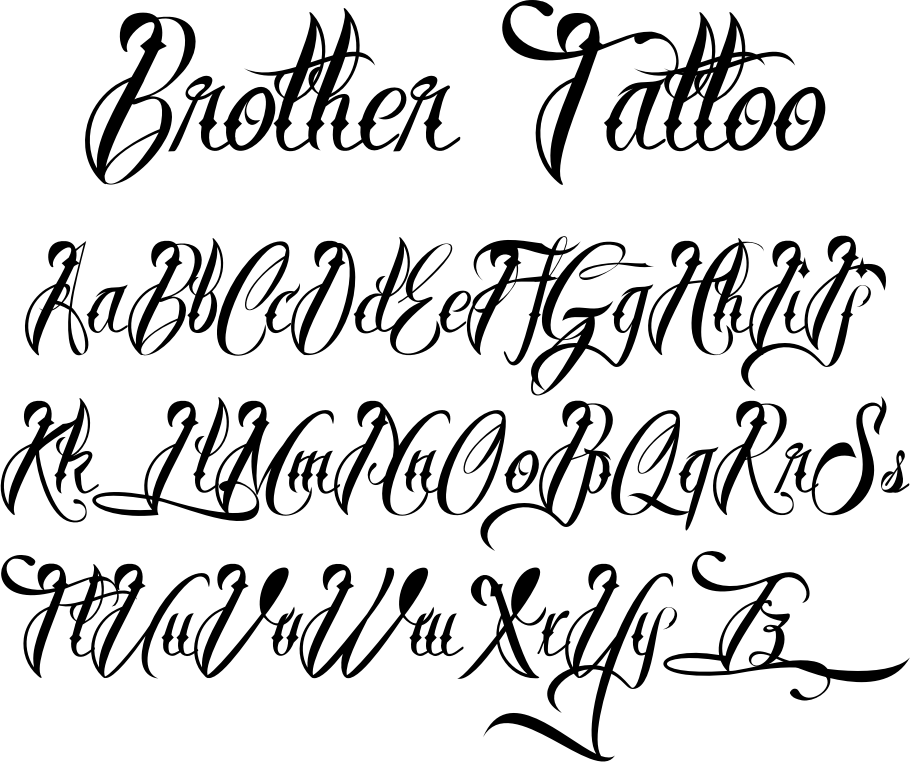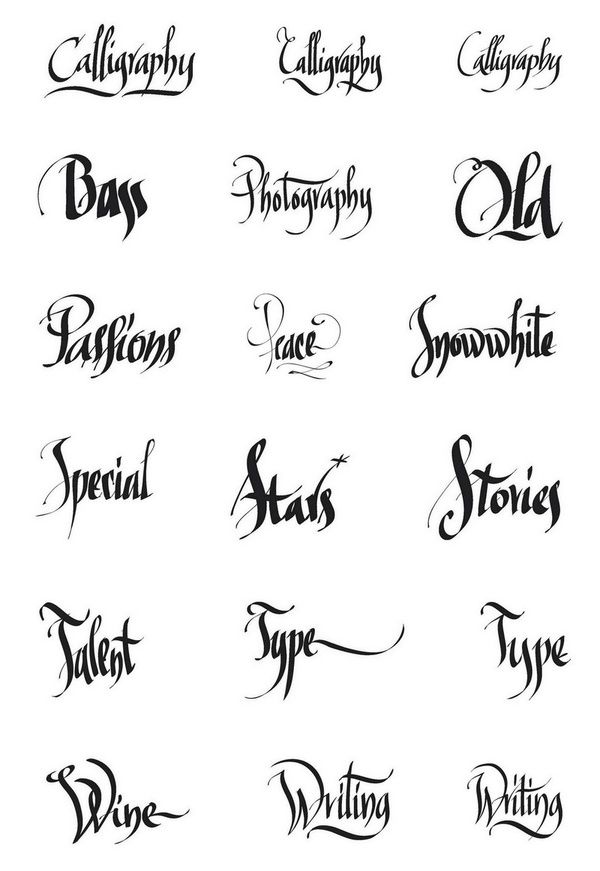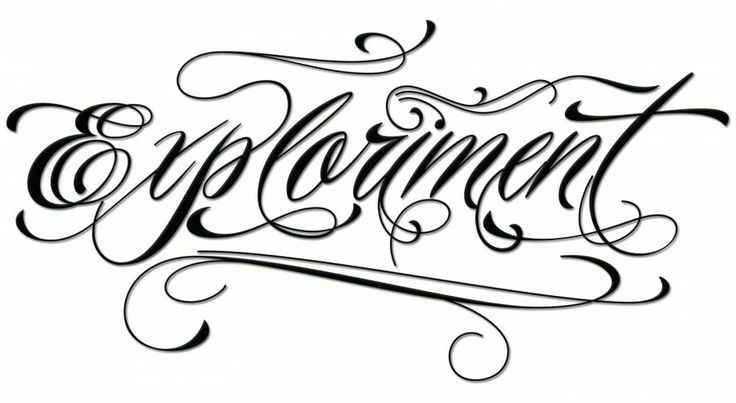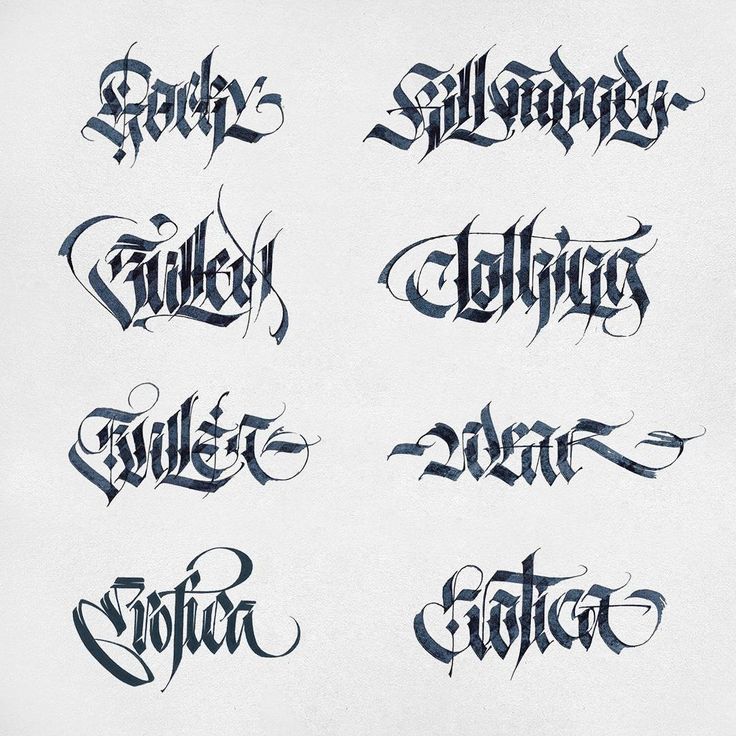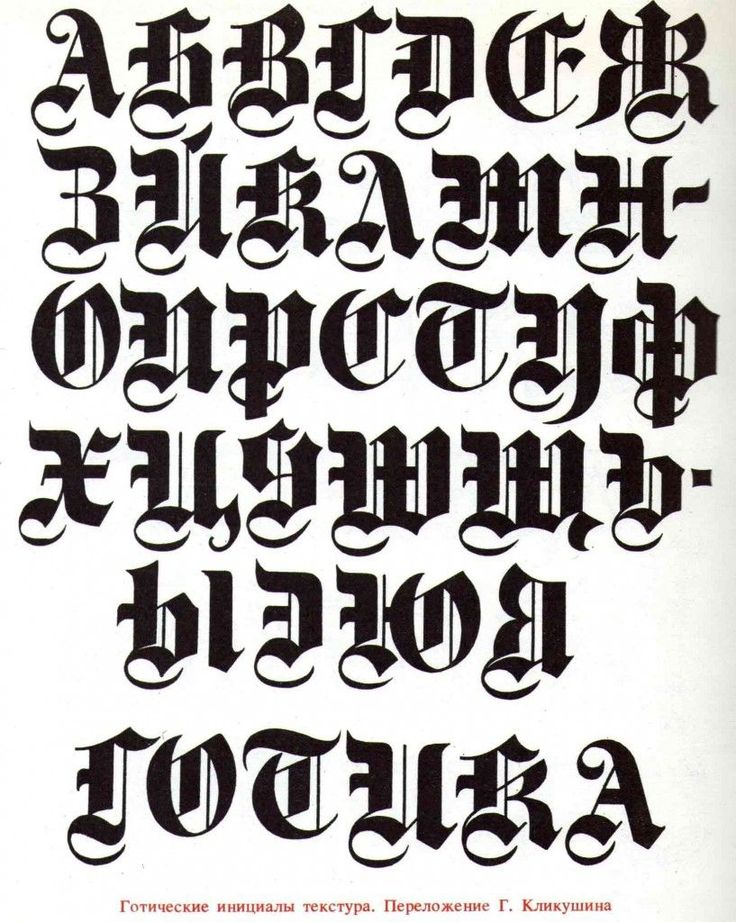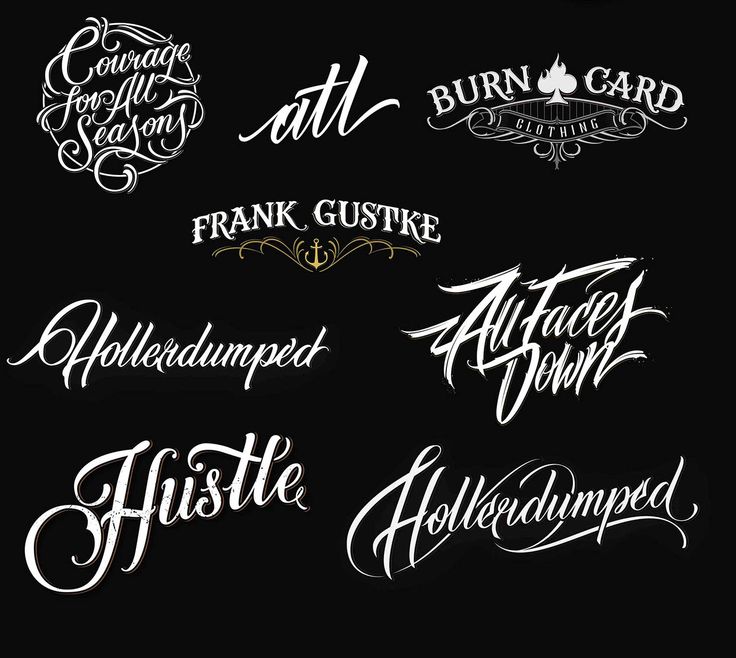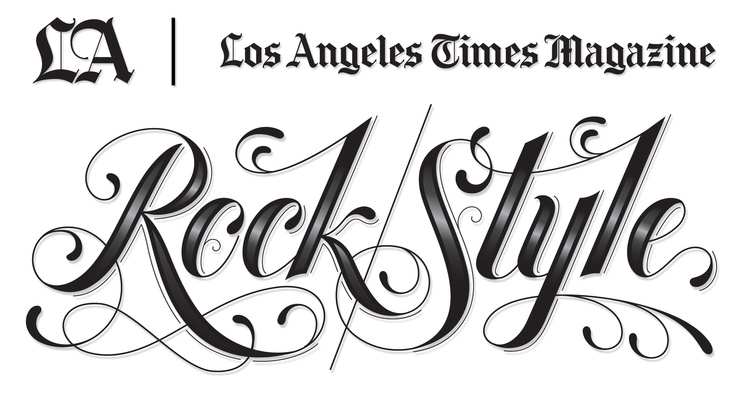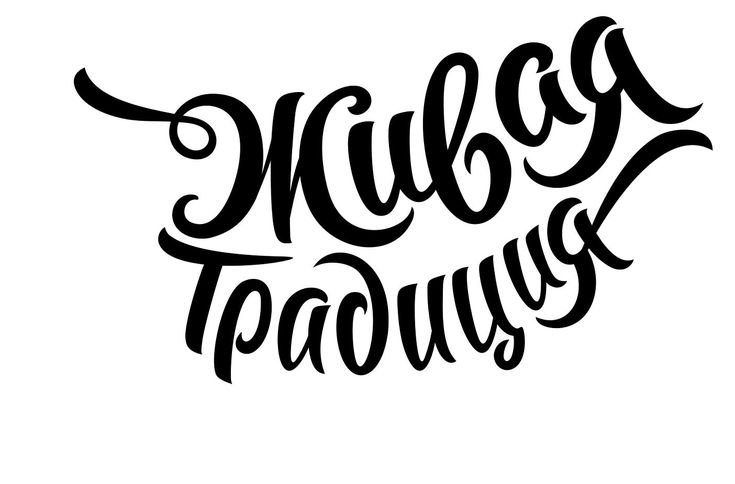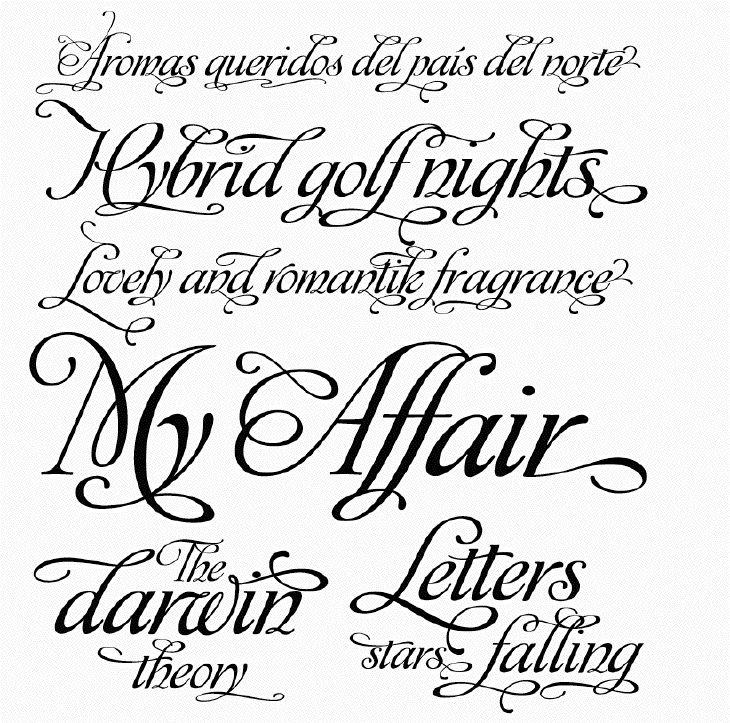
Красивые шрифты онлайн, сделать красивый текст
Шрифты являются важной частью типографики вашего проекта. Слишком причудливые буквы могут быть трудны для восприятия, слишком простые вызовут скуку и отобьют желание читать дальше. Вот почему следует максимально сосредоточиться на выборе красивых шрифтов, которые будут разборчивыми и привлекательными. Правильный фонт обеспечит эстетическую ценность контента, настроит общий тон проекта и пользовательский интерес.
Если никак не получается самостоятельно подобрать нужный стиль для дизайна текста, не волнуйтесь.
Все они отличаются индивидуальностью и разнообразием: среди них есть версии с засечками и без, рукописные, готические, курсив, печатные с поддержкой кириллицы. Цель использования таких фонтов – привлечь внимание оригинальным внешним видом. С помощью красивых шрифтов можно сделать авторскую надпись или заголовок, выделить часть текста, придав ему неповторимость и уникальность. Но для использования в основном контенте они не годятся.
К сожалению, некоторые из предложенных стилей не поддерживают русский язык, поэтому получить надпись кириллицей не всегда получается. Но таких фонтов совсем мало. С их помощью можно оформить красивый текст с элементами английского языка, что также необходимо в дизайне.
Начните работу с Ffont.ru уже сегодня и найдите шрифты, которые обязательно будут соответствовать вашему образу!
Здание говорит: архитектура и шрифт
Architecture plus font – сравнительно молодой, но популярный канал в Telegram, построенный по принципу фото-подборки: снимок здания, дополненного надписью, его название, месторасположения, год. И все. Никаких рассуждений о месте надписи на здании, о том почему именно этот кадр попал в подборку, чем конкретно удачен шрифт, на что смотреть и чем восхищаться.
В этой лаконичности канала, который ведет один из основателей бюро megabudka Кирилл Губернаторов, особая прелесть, хорошо понятная коллегам-архитекторам, которые знают, как работает такой навык, как насмотренность: ты пропускаешь через себя много-много качественных примеров, начинаешь в какой-то момент сам отличать удачные решения от неудачных, а потом и генерировать свои. Отбор контента и взял на себя канал architecture plus font.
Тема оказалась благодатной и тонкой одновременно. Архитектура — это прежде всего конструкция, но и буква — конструкция, только условно-пространственная. И в их сочетании бездны вариаций: мощная гладь стены и хрупкость надписи, массивный шрифт, «припечатывающий» здание и довлеющий над ним, шрифт-игра, тонкий шрифт, отбрасывающий тени, переливающийся ночью и скучный днем неон на неброской стене. И в каждой комбинации проступают своим символы и смыслы.